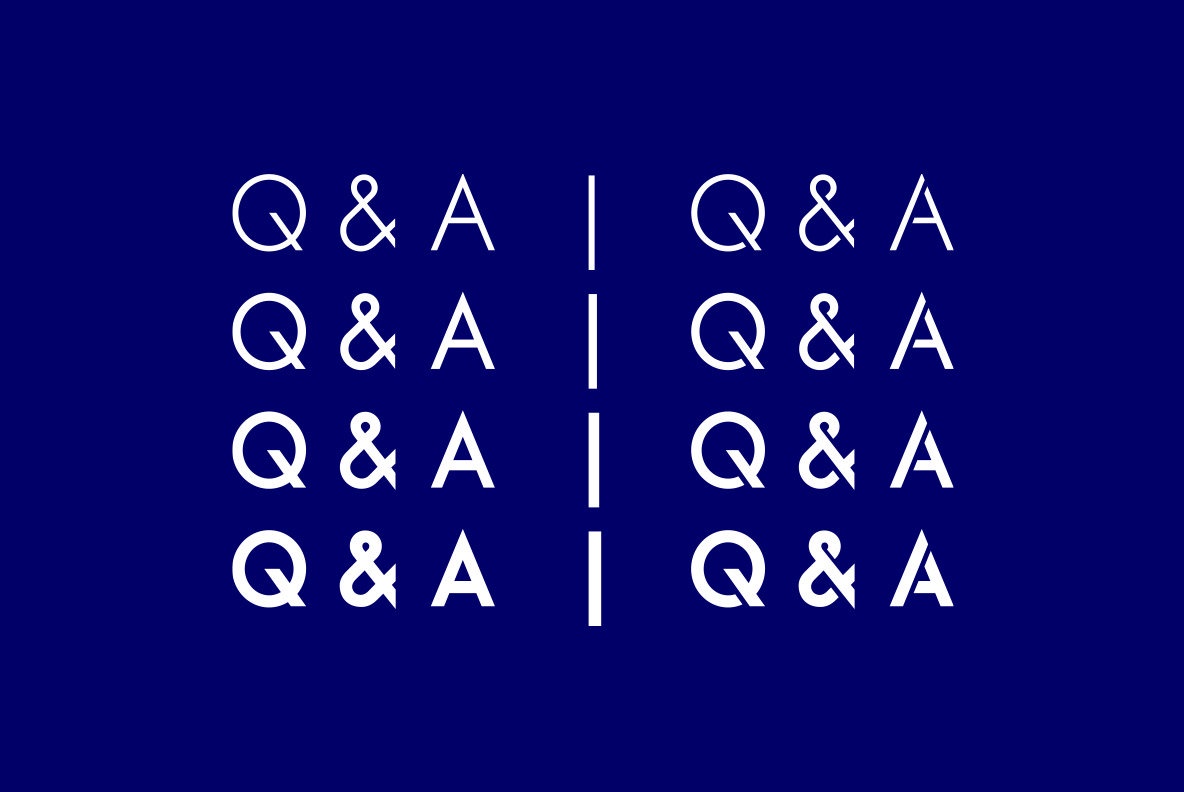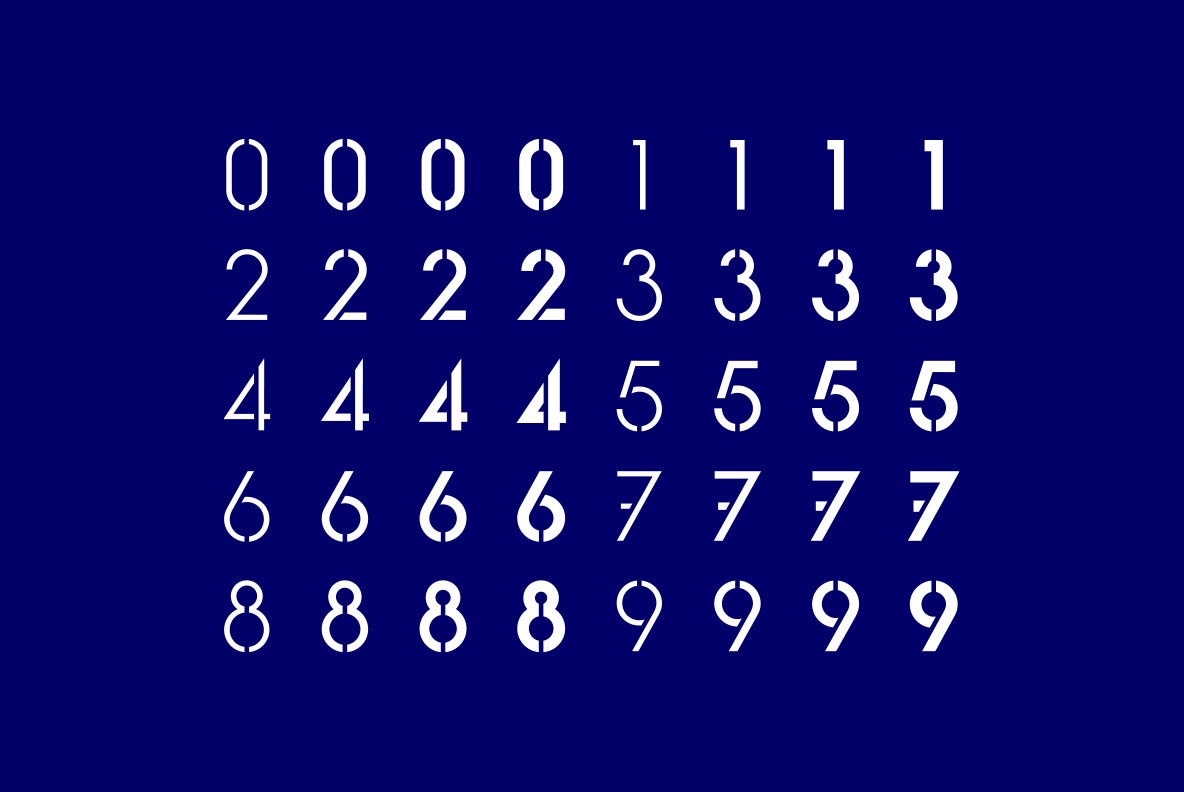
KAPITAL Font
Description de KAPITAL Font
Kapital est une élégante famille de polices majuscules sans empattement de Superfried qui a de fortes influences géométriques. Cette police se décline en deux styles distinctifs : Il existe deux types de polices : la standard et la police au pochoir. Elle est disponible en quatre épaisseurs différentes : La police contient quatre styles : léger, régulier, moyen et demi, et 346 glyphes.
Le jeu de majuscules de la version précédente, Basik, sert de base à Kapital. L’idée Kapital améliore le minimalisme de Basik et l’amène au niveau supérieur de minimalisme et de simplicité. Ce type de contrôle maintient efficacement chaque personnage en arrière-plan tout en transmettant le message de l’écrivain aux yeux du spectateur.
Une attention particulière a été portée à la cohérence des formes des glyphes selon les poids. Souvent, lorsque les polices deviennent plus lourdes, leur forme et leur design diffèrent considérablement des versions normales. Ainsi, la police Kapital résout ce problème en ayant un niveau relativement élevé de similarité de forme entre toutes les différentes graisses. De plus, le traitement des vides a fait l’objet d’une grande attention. Un certain degré d’espace négatif est inévitable ; cependant, les concepteurs ont apporté les modifications appropriées aux formes des lettres pour réduire le phénomène et obtenir un design plus harmonieux dans l’ensemble de la police.